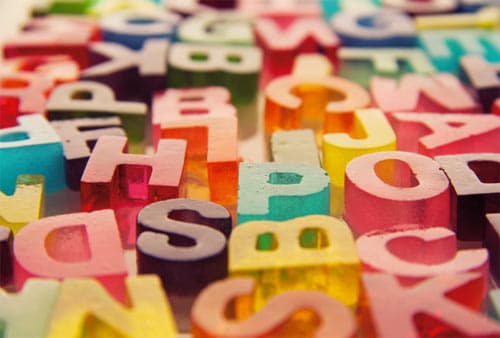
Tipografías muy dulces
Sweet Letters 1
Hoy en Diario THC les quiero hablar de nuevo de tipografías. Aunque en este caso no les traigo un recurso que se pueden descargar para su Photoshop o sus programas de diseño vectorial, si no de una imagen que dice mucho más que tantas palabras en la cual podemos ver un diseño muy curioso de tipografía en el que inspirarnos para crear las nuestras propias.
Y es que esta tipografía tan dulce sin duda podría ser perfecta de cara a hacer logotipos de marcas infantiles, relacionadas con el mundo de los pasteles, o incluso porque no de aquellas que tengan la diversión e primer plano. Y en el mundo de la gráfica publicitaria y de promoción tendría todavía muchas más aplicaciones.
Aunque justo al final del post les dejo el link en el que pueden ampliar información acerca de esta tipografía tan dulce de las diseñadoras industriales Aranxa Esteve y Lucía Rallo,  lo cierto es que es una fuente de inspiración para que cualquier cosa de la realidad la podamos llevar al mundo tipográfico y quien sabe si acabar sorprendiendo como han hecho estas dos chicas. ¿Qué me dicen, se atreven a sacarle jugo a las neuronas?